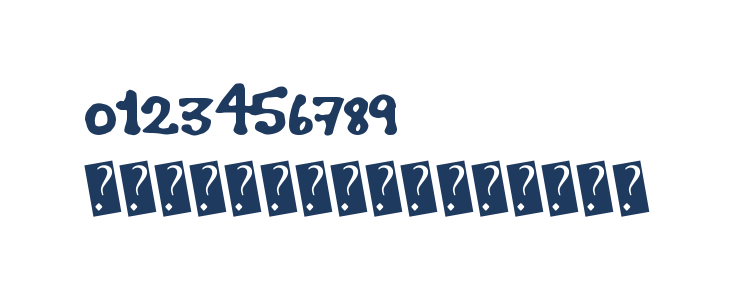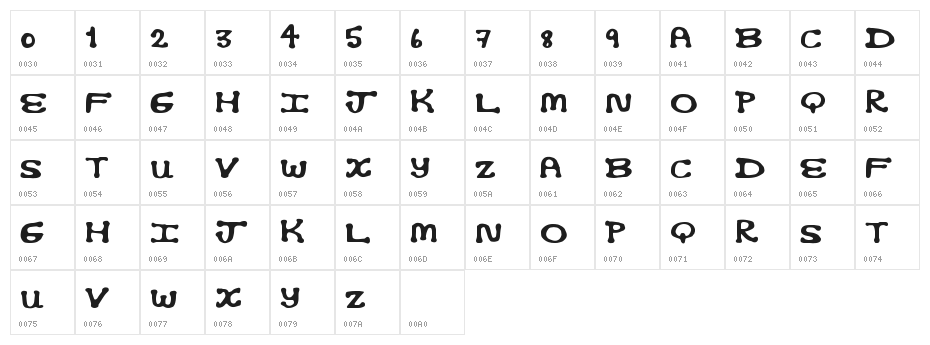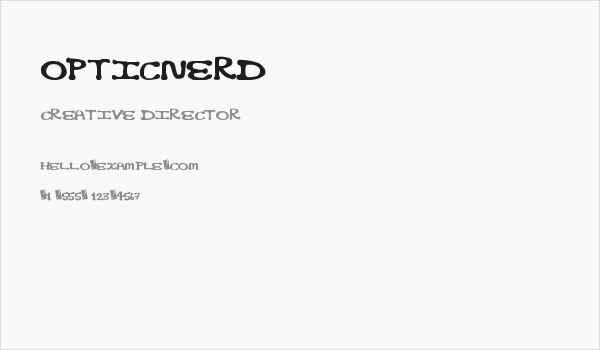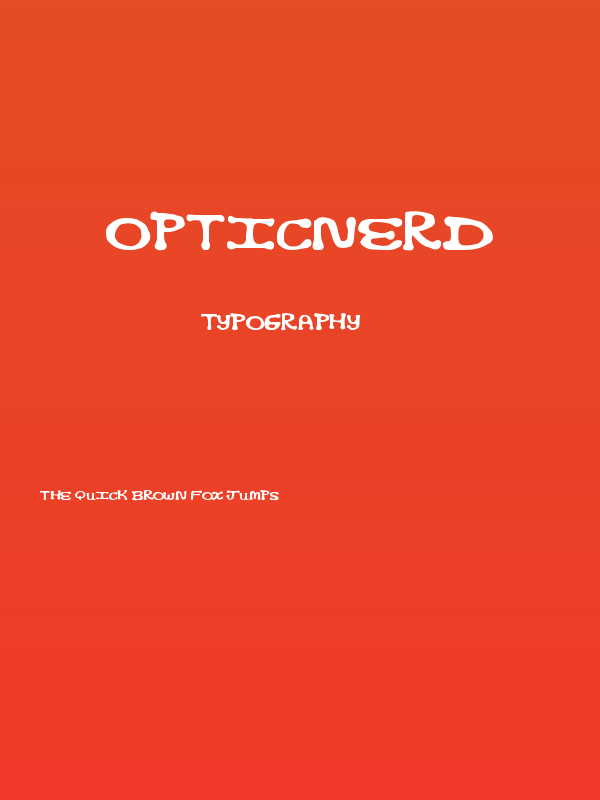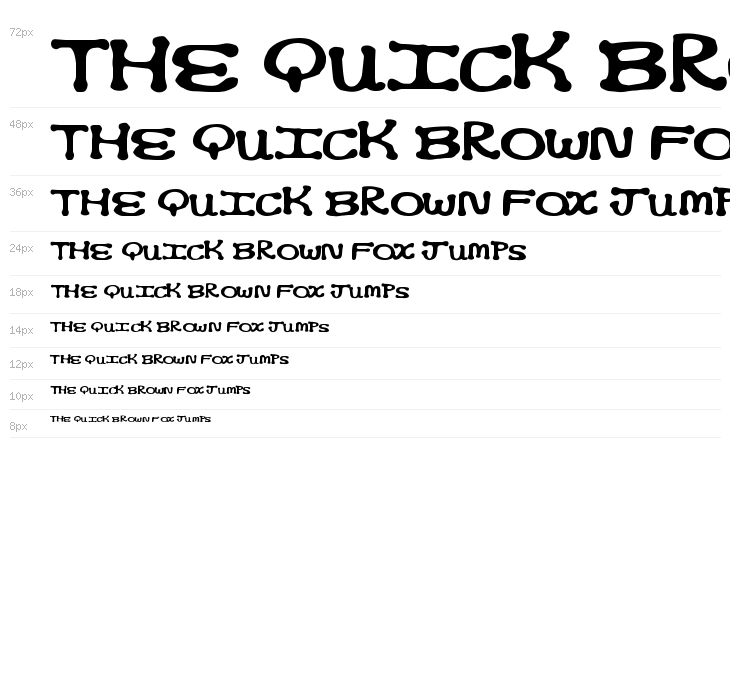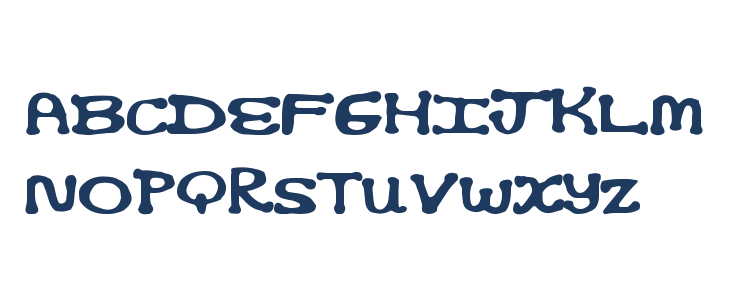
OpticNerd Font
✎ Cartoon
| Gesamtstil | Playful, Quirky, Hand-drawn |
| Anwendungsfall | Headlines, Posters, Creative projects |
| Vorgeschlagene Projekte | Ideal for children's books, playful branding, creative posters, and informal invitations. |